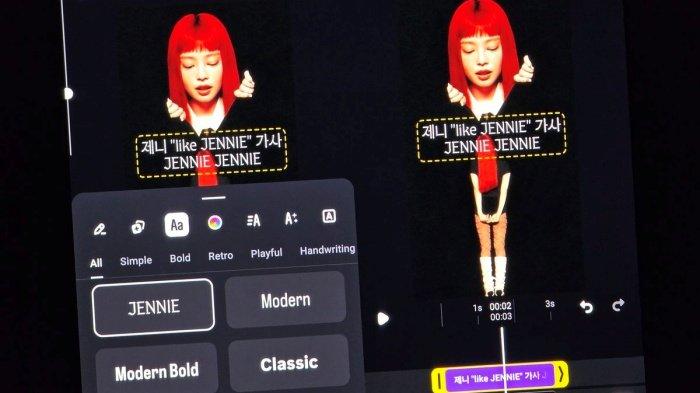
Jennie BLACKPINK Luncurkan Font Zen Serif, Ini Link Downloadnya, Gratis
Jennie BLACKPINK luncurkan font Zen Serif, ini link downloadnya, gratis.
TRIBUNKALTIM.CO - Anggota BLACKPINK, Jennie Kim, merayakan Hari Hangul yang jatuh setiap 9 Oktober dengan cara yang unik dan kreatif.
Hangul adalah nama dari huruf Korea.
Melalui labelnya, OA (Oddatelier) Entertainment, Jennie memperkenalkan font baru bernama Zen Serif, yang dirancang untuk memperkenalkan keindahan aksara Korea kepada dunia.
Font adalah bentuk huruf yang memiliki gaya, ukuran, dan ketebalan tertentu.
Mengenalkan Hangul Lewat Estetika Tipografi
Dalam pernyataan resmi OA Entertainment, Zen Serif diciptakan dengan harapan agar lebih banyak orang mengenal Hangul tidak hanya sebagai sistem tulisan yang efisien, tetapi juga sebagai bentuk seni visual yang elegan.
Font ini menjadi bagian dari upaya Jennie untuk mempromosikan budaya Korea melalui pendekatan desain dan estetika.
“Zen Serif hadir untuk menunjukkan bahwa Hangul bisa tampil indah dan modern, tanpa kehilangan nuansa tradisionalnya,” tulis OA Entertainment.
Filosofi “Zen” dalam Gaya Hidup dan Desain
Nama “Zen” bukan hal baru dalam karya Jennie. Sebelumnya, ia menggunakan istilah tersebut sebagai judul lagu dalam album solonya Ruby yang dirilis Maret 2025.
Secara etimologis, “Zen” berasal dari bahasa Jepang yang berakar dari istilah Tionghoa “Chan”, yang berarti meditasi atau ketenangan batin.
Dalam budaya populer, kata ini sering diasosiasikan dengan kesederhanaan, keseimbangan, dan kesadaran penuh—nilai-nilai yang juga tercermin dalam gaya hidup dan citra Jennie.
Zen Serif mengusung gaya serif klasik—jenis huruf dengan garis kecil di ujung tiap karakter—yang sering diasosiasikan dengan kesan formal dan elegan.
Namun, Jennie dan tim desainnya menambahkan sentuhan kaligrafi ala huruf hitam (blackletter) serta kelembutan khas Hangul, menciptakan perpaduan antara nuansa modern dan tradisional.
Kolaborasi Global dengan Meta